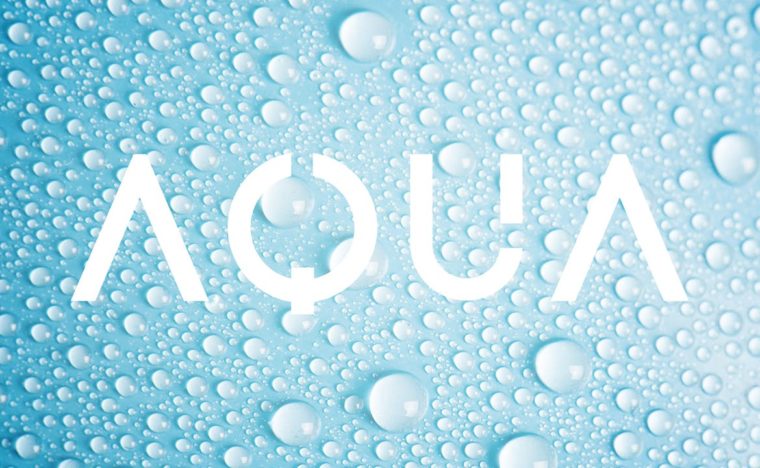
【Font for music】EDM等の音楽ジャンル別の最適フォントスタイル2018年版20選!あなたの音楽の世界観を視覚的にも表現
音楽は独自の世界観を作ります。
また、あなたの音楽プロジェクトもあなただけの世界観があります。
人は視覚的な刺激に影響されます。
たとえ良い音色を持っていたとしても、フォントに関して正しい美学を持っていなければ、人々はあなたの音楽を心からは聞かないかもしれません。
音楽をフォントから視覚的に感じてもらうにはどうコントロールするのか考えてみましょう。
すでにご存知のように、音楽のジャンルは非常に定義されそれぞれのスタイルや感覚があります。
この記事では、最も人気のある5つのジャンル(EDM、カントリー・ミュージック、ヒップホップ、ポップ、ロック)のミュージックビデオのフォント(Envato Elementsより)を考察します。
これは音楽プロジェクトを始めたばかりでその音楽に似合うスタイルを探しているアーティストのガイドになります。
EDM
あなたの音楽が巨大なスクリーン、花火、レーザーで華やかに彩られ、ライブやフェスティバルまたはクラブで演奏されている事を想像してみましょう。
その時あなたはダンスミュージック(EDM)、音楽の流れに身を任せているでしょう。
このジャンルは、明るい色、楽しみ、そして高度に統合された技術に関連しています。
そしてこのジャンルに似合うフォントがいくつかあります。
Dreamscape
このフォントは、SF映画のような雰囲気を持ちます。
未来的、空間を引き伸ばされたような、現代のEDMプロジェクトととても相性が良いです。
Top Light Brush
このフォントは、EDMが持つ面白さを表現することができます。
そしてMartin Garrix-typeの音楽や壁に書かれた落書きのようなインスピレーションと大きなエネルギーを連想させます。
AOKI
このフォントは少し疑わしい雰囲気です。
スティーブアオキはおそらく最大のEDMの支持者です。
きれいな線と丸みのある美学を感じ取ることができれば、選ぶ意味があるでしょう。
Karma
これらのサンシェードは近年とても人気があるのを知っていますか(特にEDMコミュニティで…)?
この幾何学的で未来的なフォントは、EDMプロジェクトで大変期待されています。
カントリー
あなたの音楽は愛や憎しみ、伝統、人生、死、バー、戦い、馬、そして多くの非常に個人的な事柄について表現していますか?
伴奏は太鼓のボーカル、バンジョー、ハーモニカですか?
少し定型的かもしれませんがカントリーミュージックはこれらの要素が1つ以上あります。
もしそうであると感じたら、是非このフォントを使ってみましょう!
Bakersville
この手書きの書体は、視聴者にWild Westを連想させます。
音楽プロジェクトのロゴ、デザイン、ミュージックビデオ、CDアートなどに最適なフォントです。
Premier Sans
Premier Sansはインディーズなカントリーミュージックのプロジェクトでよく使われています。
昔のアイスクリーム売店や、バーで使用されているような雰囲気で、書体に楽しいひねりがあります。
Lawless
Lawlessはカントリーミュージックの共通の言語であなたのプロジェクトにぴったりです。
それに加え、その手描きのフォントは1800年代のWild West の雰囲気をも持ち合わせています。
Gilly
そしてアメリカンウェスタンのテイストを入れたい場合、より流動的で洗練された表情が出せます。Gilly使ってみましょう。
Hip Hop
‘I said hip hop, the hippy, to the hip, hip hop and you don’t stop…..’
「私はHip Hop、hippy、hippy、Hip、Hip Hop….と言う…そして止まらない…」
The Sugarhill Gangの “Rapper’s Delight” の歌詞から、ヒップホップは単なる音楽ジャンルではないことが分かります。 サブカルチャーです。
結果として、美学とスタイルに大きな影響を受ける、定義されたスタイルを持っています。
それを表すような、ヒップホップに似合うフォントがいくつかあります。
Rander
グラフィティには大きな影響があります。
古典的なヒップホップ要素を持つフリーハンドのラフなブラシフォントである ‘Radical’ を見てみましょう。
Haarlem Deco
ブロンクスはヒップホップの発祥の地です。ハールレムと言う地域はブロンクスの南にあるので、Haarlem Decoをこのリストに含めています。
さらに、このアールデコの書体は、高級ラッパーのためのヴィンテージな雰囲気を演出します。
Velociraptype
あなたが伝えたい物がストリートの要素を持ったものの場合、落書きタグを連想させるクールで未来的な雰囲気がある”Velociraptor” を使ってみましょう。
Winsor
一方、WinsorはBlackletterは強いラインとゴシック感があり、ヒップホップのスタイルでも使えます。
Pop
ポップミュージックは幅広い意味合いがあるので一言で定義するのが難しいジャンルです。
しかし、その主な目的は非常に具体的で一貫した音楽式で大衆にアピールすることだと言えます。 これは、ポップミュージックの美学です。 そしてそれを示唆したり挑戦する以上に、すべての傾向を追うことです。
あなたの音楽ビデオフォント、またはポップミュージックプロジェクトのあらゆる面で使用する書体とこのアイデアを一致させるには、次に紹介するフォントを調べて見ましょう:
Porta
あなたのポップミュージックプロジェクトが創造的で楽しい旋律を持っているなら、それは幾何学的、未来的、バランスの取れた、そしてミニマルな美学を持っています。
Portaはそれを表現する書体です。
Venge
もしあなたが流行に乗った音楽を創造している場合、Vengeはあなたが望むファッショナブルなポップなスタイルを与えます。
あなたは最もスタイリッシュなポップスターになることができます!!
Be Greatful
ポップミュージックはエレガントで上品な側面を持っていて、かつてないほど魅力的な音楽です。 あなたがそう思うなら、商品やロゴなどに使うことができる、”Be Grateful”フォントを使ってみましょう。
SF Kingston
このSerif Didoneの書体はモダンでビンテージなルック・アンド・フィールを強調しています。円形と三角形のコンポーネントで流れ、同様のポップミュージックプロジェクトで使われます。
Rock
ロックのジャンルも幅が広いので表すのが難しく一概に定義できないジャンルです。
ブラックデスメタルからパンク、シューゲイザーまでロックとみなされることがあり、なぜここまで複雑かと言うと、ロックに含まれるジャンルがそれぞれにまた異なる美学やスタイルを持つからです。
では、ここからはロックに似合うフォントを紹介します。
The Crow
The Crowはとてもいいアイデアを与えてくれます。
汚れ、暗い、危険で激しい感じですが、興味深ですね。
Funkrocker
このFunkrockerですが、実際のパンクの雰囲気を提供します。
ちょっと厄介で、荒縁、都会的でとても元気な雰囲気さえ感じます。
すべてのフォントがパンク・ミュージックに合う可能性があります。
Dead Marine
誰もが入れ墨をすることはできますが、ロックは彼らと特別な関係を持っています。 ”Dead Marine” は、あなたの音楽プロジェクトのビジュアルデザインに完全に合うビンテージのタトゥーのインスピレーションを引き出します。
Moody Blue
最後に”Moody Blue” は斬新で神秘的でエレガントで楽しいフォントです。 それだけでなく使い方によっては、暗くて軽い感じも出すことができます。